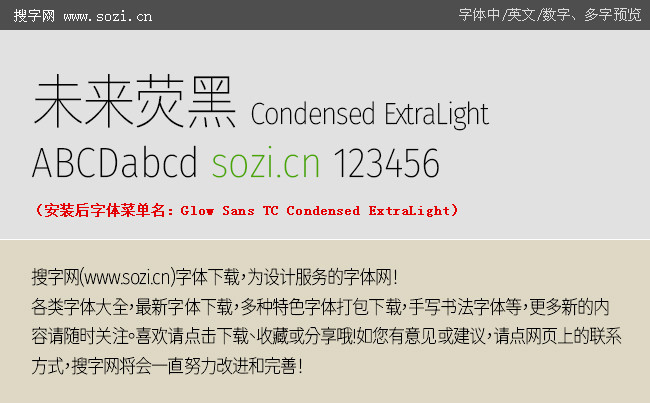
未來熒黑GlowSansTC-Condensed-ExtraLight
搜字網(wǎng)給大家提供一款未來熒黑GlowSansTC-Condensed-ExtraLight中文字體下載,未來熒黑GlowSansTC-Condensed版是未來熒黑中的一個瘦長體系列,未來熒黑是一個基于思源黑體、Fira Sans和Raleway的開源字體項目,該字體由八種字重,字體中宮與字面更加收斂,細(xì)節(jié)上面處理更加的干練,適合應(yīng)用于藝術(shù)設(shè)計、平面宣傳設(shè)計、網(wǎng)頁設(shè)計等廣告設(shè)計。